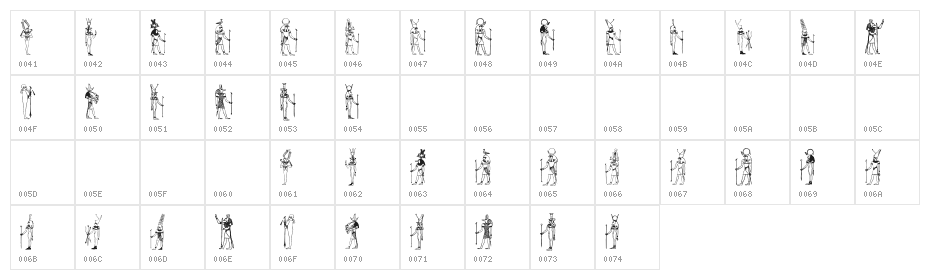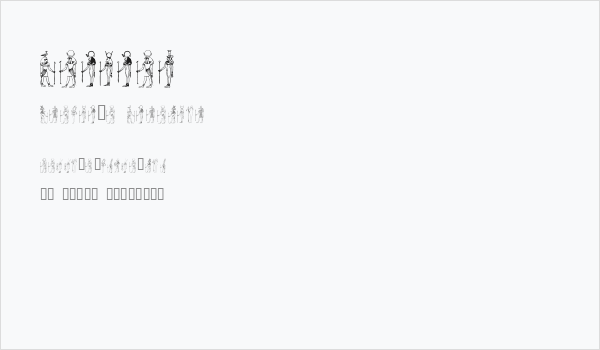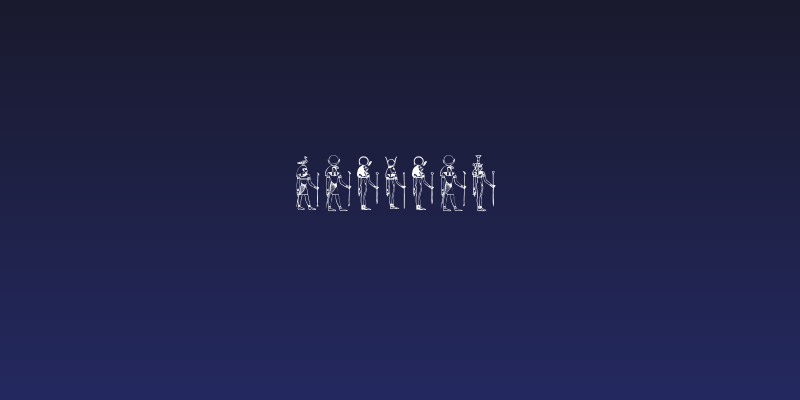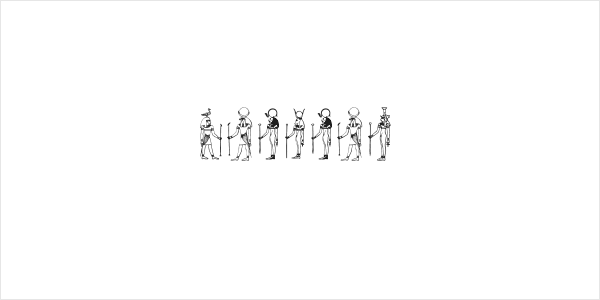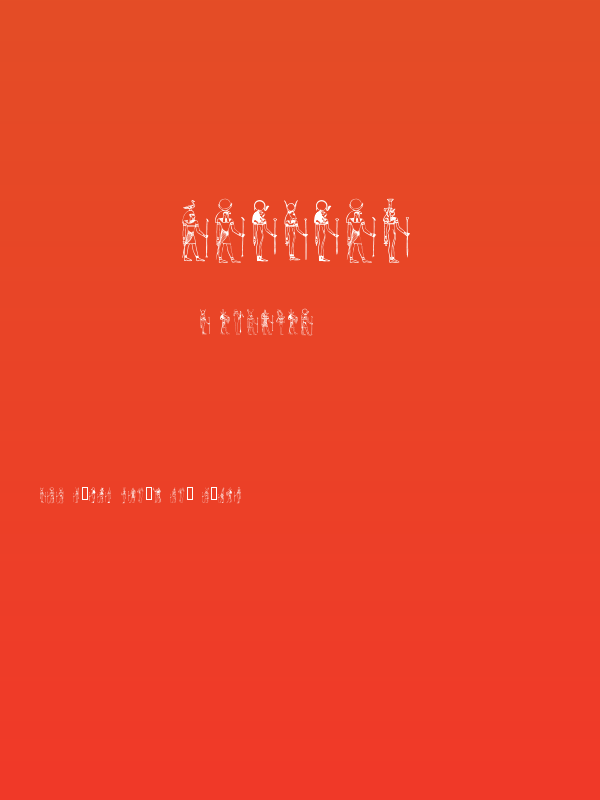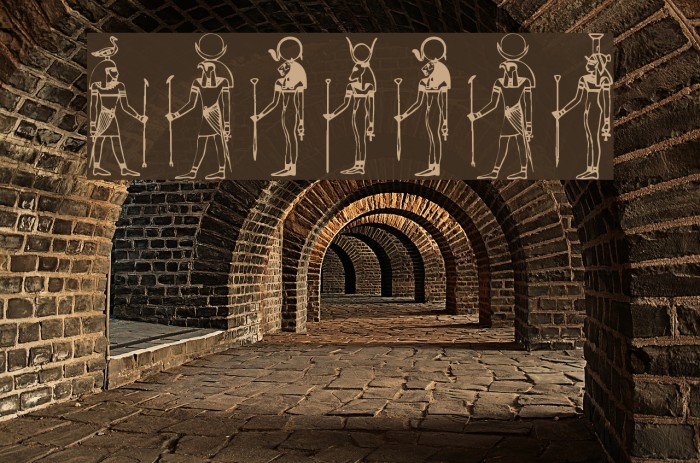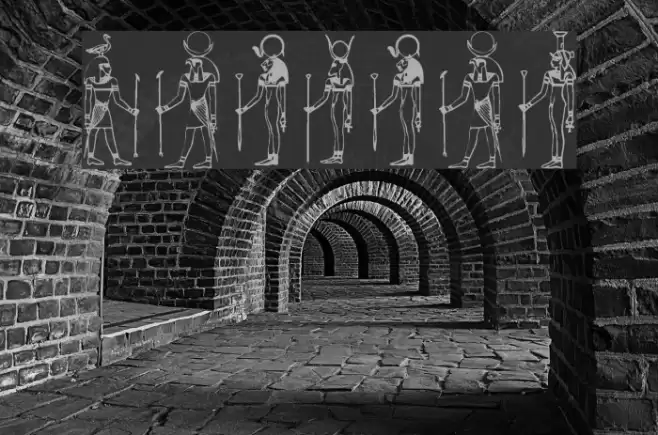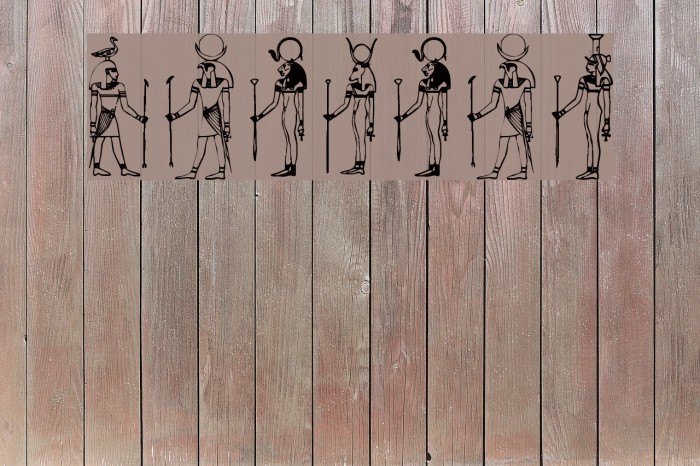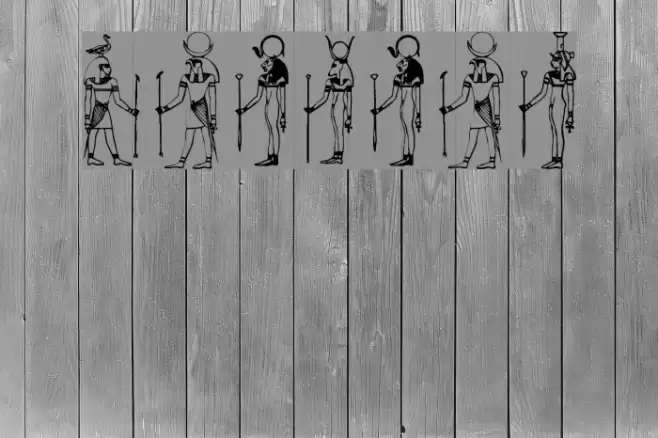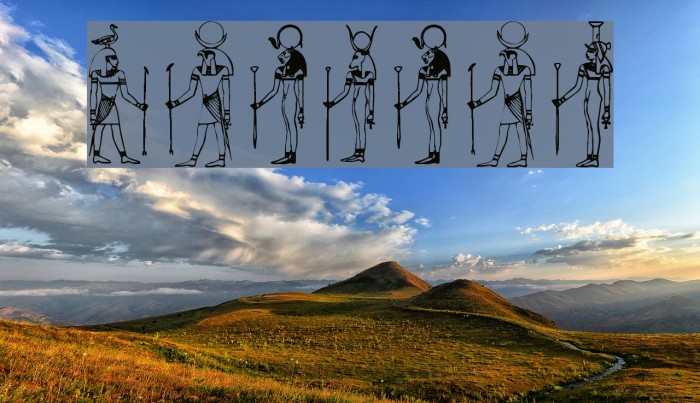
Deities Font
| Gesamtstil | Decorative, Thematic, Historical |
| Anwendungsfall | Logos, Headlines, Posters, Themed graphics |
| Vorgeschlagene Projekte | Museum exhibits, educational posters, themed event invitations, historical fiction book covers, cultural branding. |